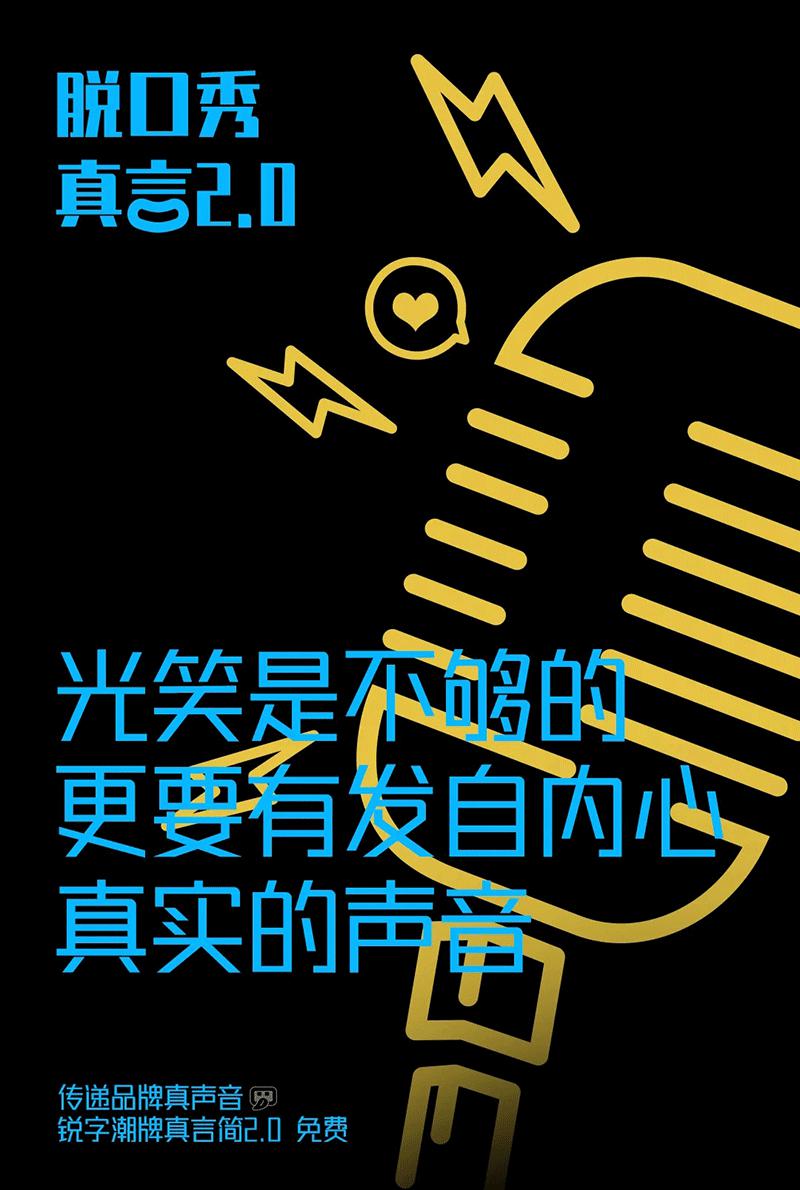
锐字潮牌真言体
锐字潮牌真言体2.0,支持可变字体
字体介绍
锐字潮牌字库成立7周年重磅官宣:锐字潮牌真言简2.0全新升级发布!免费商用!
本次升级调整字体结构;新增6个字重;增加17个繁体与生僻的常用字,共7672个字符。并支持可变字体!可随心所欲自由变换,把字体玩出花!现面向社会开放下载,
品牌真言,即品牌灵魂。锐字潮牌真言简2.0免费,在1.0版本基础上进行视觉升级,全方位展现品牌信息,更好地传递品牌真声音。
更具呼吸感、通用性更强:锐字潮牌真言简2.0细体文字,结构干净,笔画移除了粗细对比,因此辨识度更高,字形看起来更加清晰、干净。中性的笔画设计与分隔使得细体文字通用性更强,排版也更有质感,画面看上去更加轻盈,具有呼吸感,更容易阅读。
系列化字体、更加潮流、高级:升级后的系列化字体,在保持横画不变的基础上,将竖画粗细进行变化,随着字重的减小,横画与竖画粗细对比减弱,增添了字的留白与内部空间感,给人潮流、高级之感。
6字重全方位免费、传播品牌真声音:品牌声音也有跨度,从低声吟唱到放声高歌,你的品牌要跨越几个度?
锐字潮牌真言简2.0在1.0版本基础上,衍生出5款系列化字体,共细体、常规、准粗、大粗、特粗、超粗6款字重,全面传播品牌真声音。
潮牌可变字体、拥抱变化新世界:本次字体升级的另一个惊喜:新增可变字体技术!将含有字体粗细变化的字体文件,包含在单个字体文件中,从而实现随意切换,让字体呈现出不同的形态。
字体自由变换,具有无限延伸的可能性,安装可变字体文件后,可以通过滑动调节字体的粗细,在这种自由的形态下,设计师可以按照设计需求、喜好来控制字体的使用范围,让字体具有无限延伸的可能性。
更灵活的使用场景,全新的视觉体验,可变字体的应用,突破了传统字体的限制,比如网页适配,不同的显示器设备屏幕比例适配等,让字体在不同的传播媒介中可以更灵活地运用。
除此之外,可变字体还拥有更多的创意空间与可能性,为品牌带来全新的视觉体验。
体积更小,更节省存储空间,一般传统字库里6个字重,分别以独立的形式存储,所占空间大概是8.24MB,而一款支持可变字体的文件仅需2M,减少了字体文件的大小,存储空间大大提升。
潮牌可变字体新纪元,拥抱场景变化新世界:当前,可变字体已成为设计领域的一个热点,将可变字体运用到多维虚拟世界中,会发生什么?
字体应用范围更加广泛,适用于文字标题、广告设计、个性品牌设计推广、企业宣传及时尚品牌的设计应用,从电商、产品到视频、直播等领域,带给用户新的体验和感受。